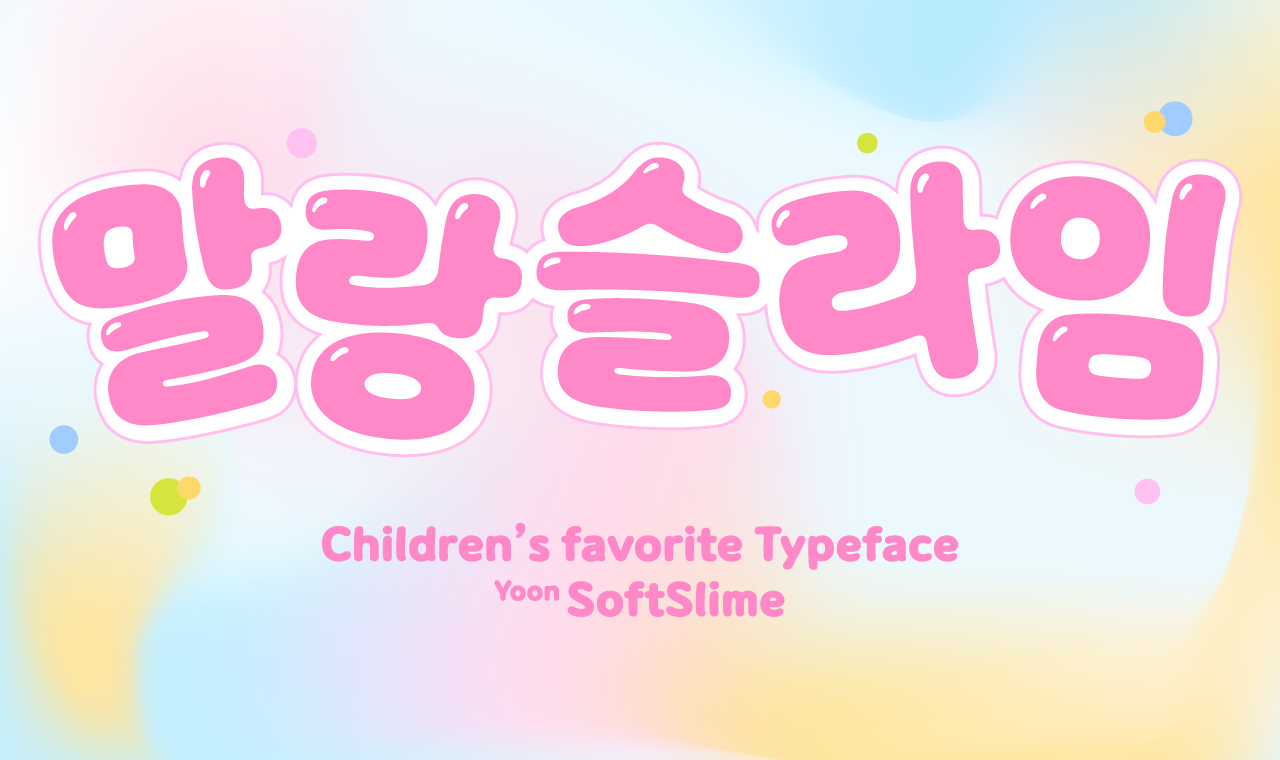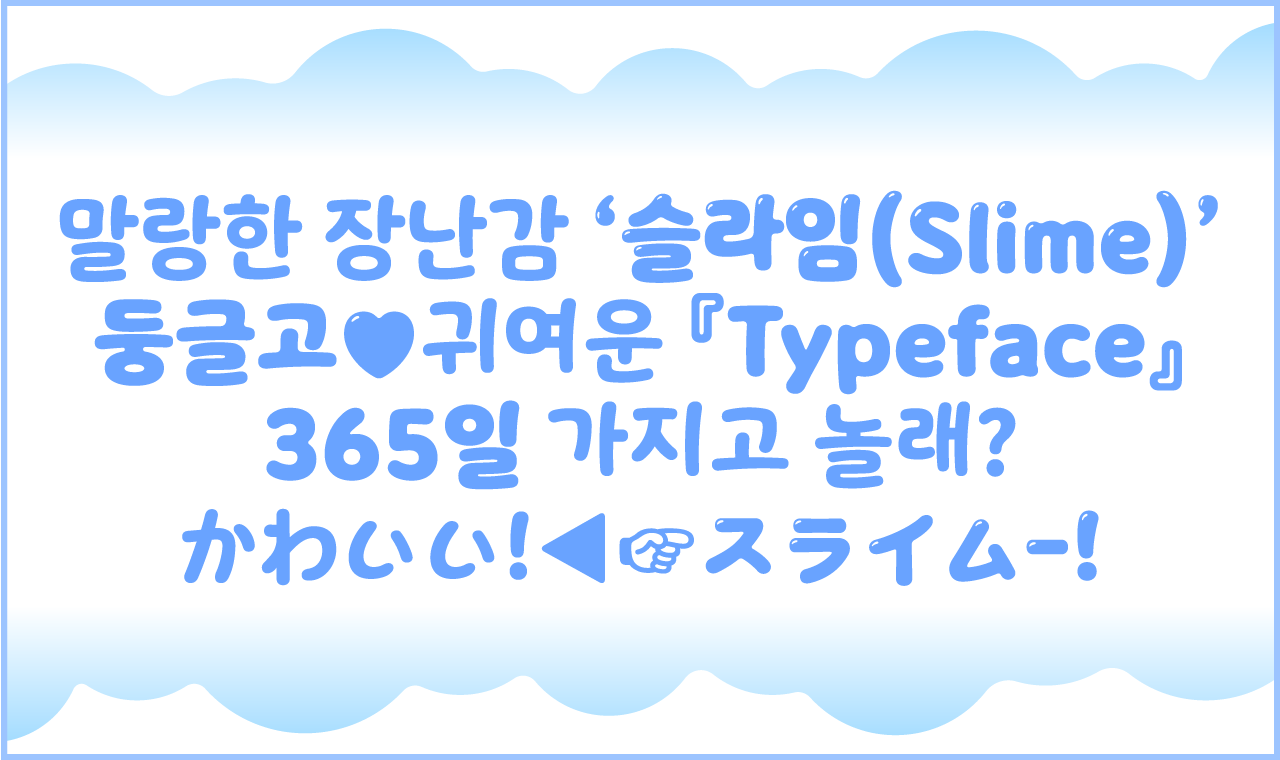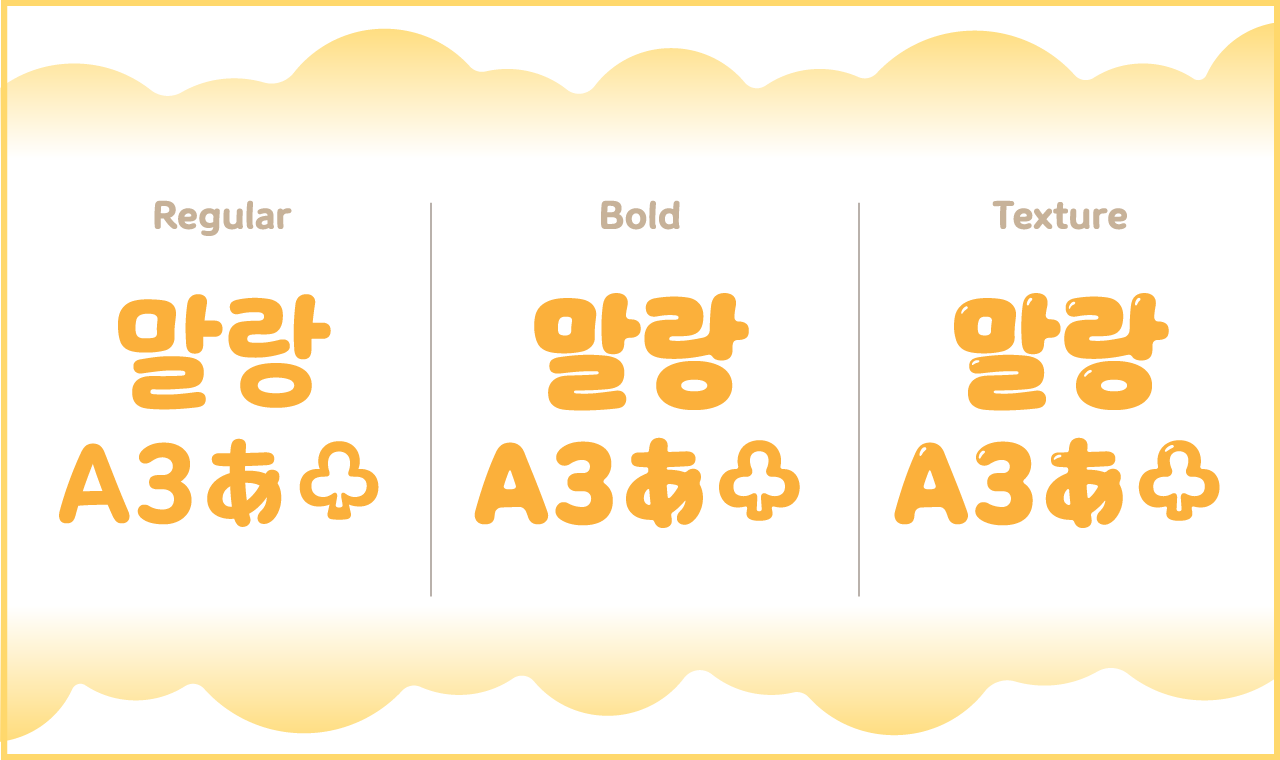
‘말랑슬라임’은 아이들 장난감 슬라임을 콘셉트로 작업한 서체입니다. 유튜브, 스트리밍 등 모바일 기기와 친숙한 알파세대를 타겟으로 작업했으며 자막으로 사용하기 좋은 Regular와 제목으로 사용하기 좋은 Bold, Texture로 구성되어 있습니다. 동글동글하며 손글씨 느낌으로 귀엽고 통통 튀는 매력이 있는 서체입니다.
Yoon 말랑슬라임